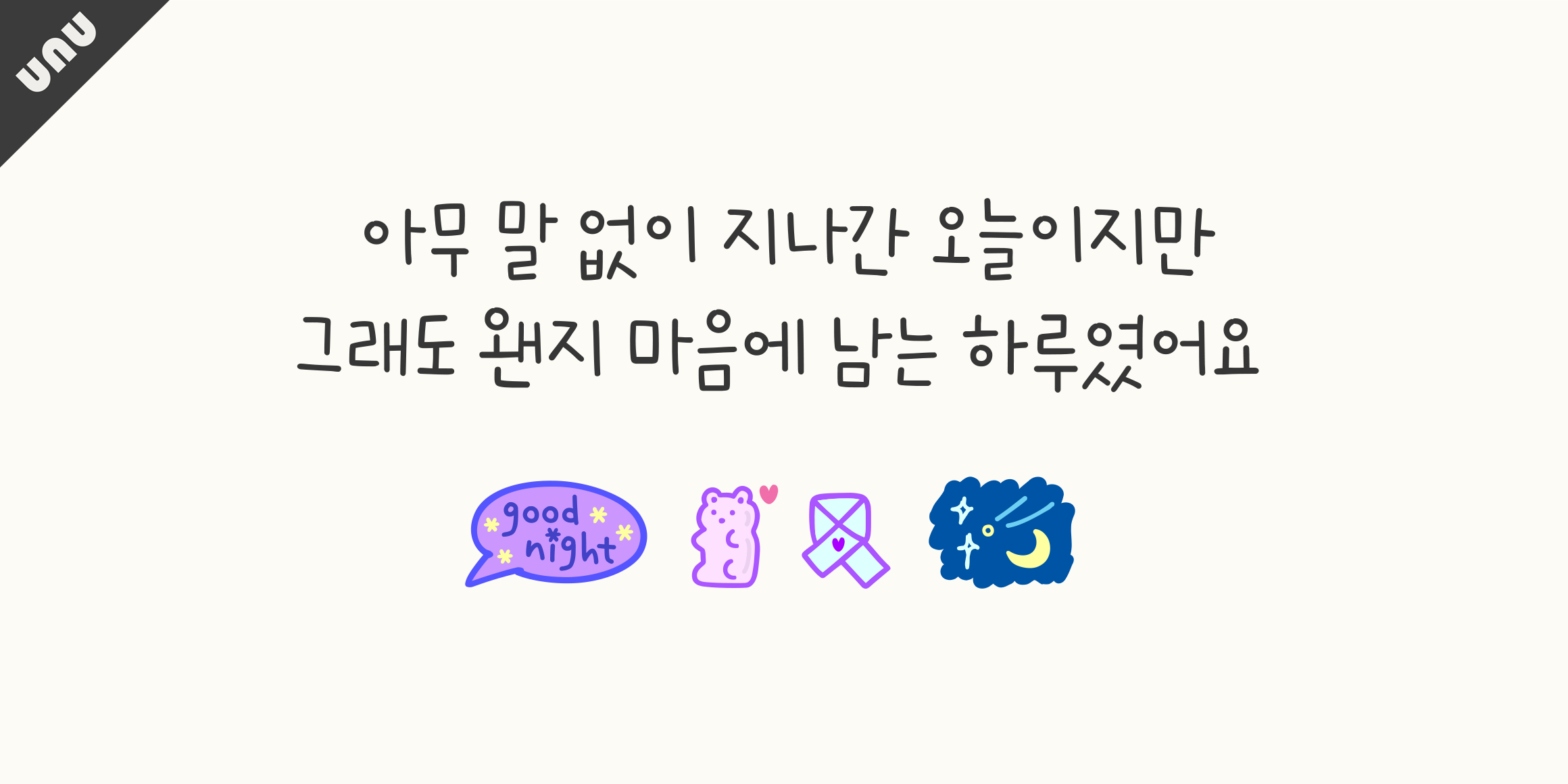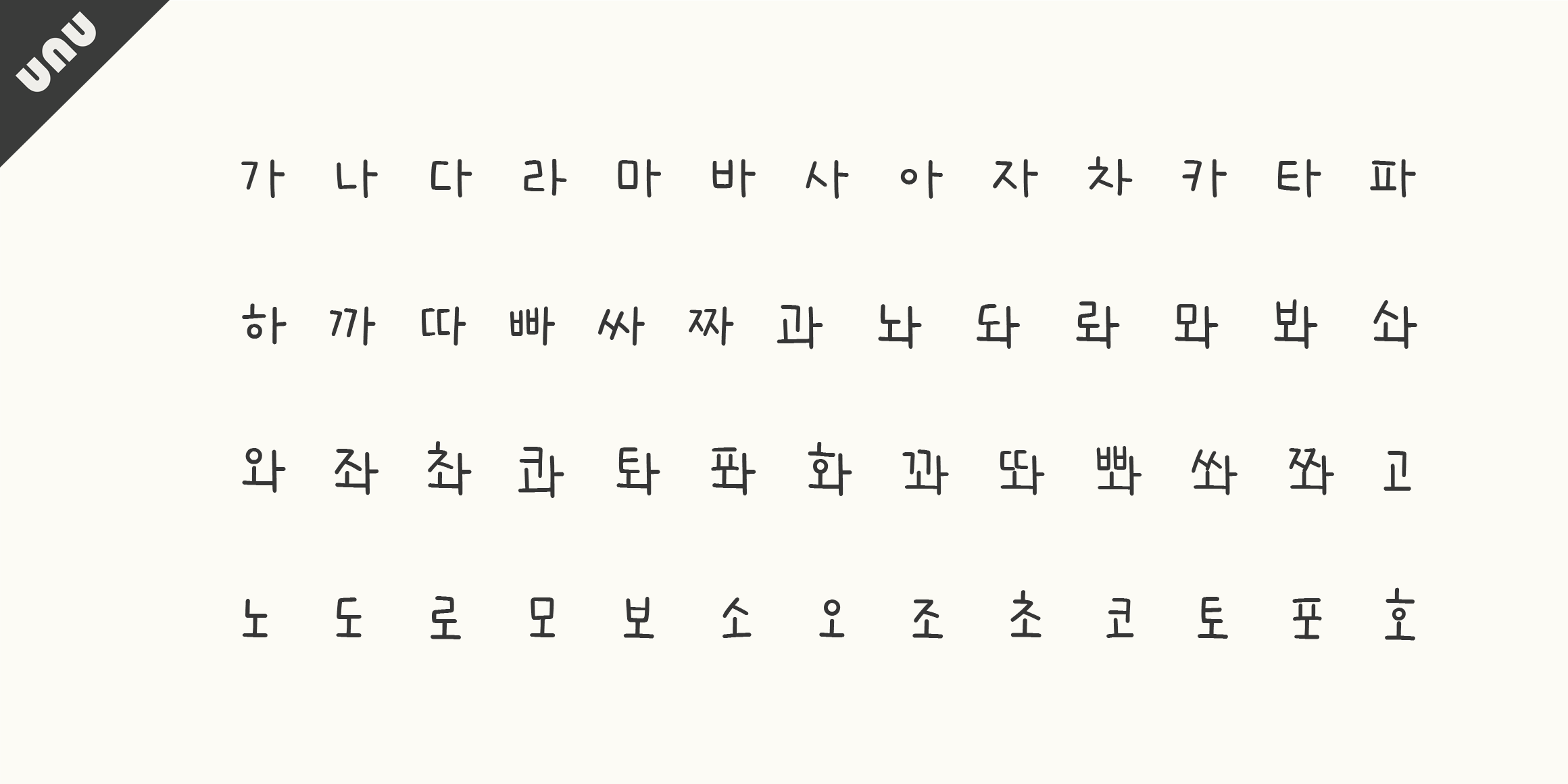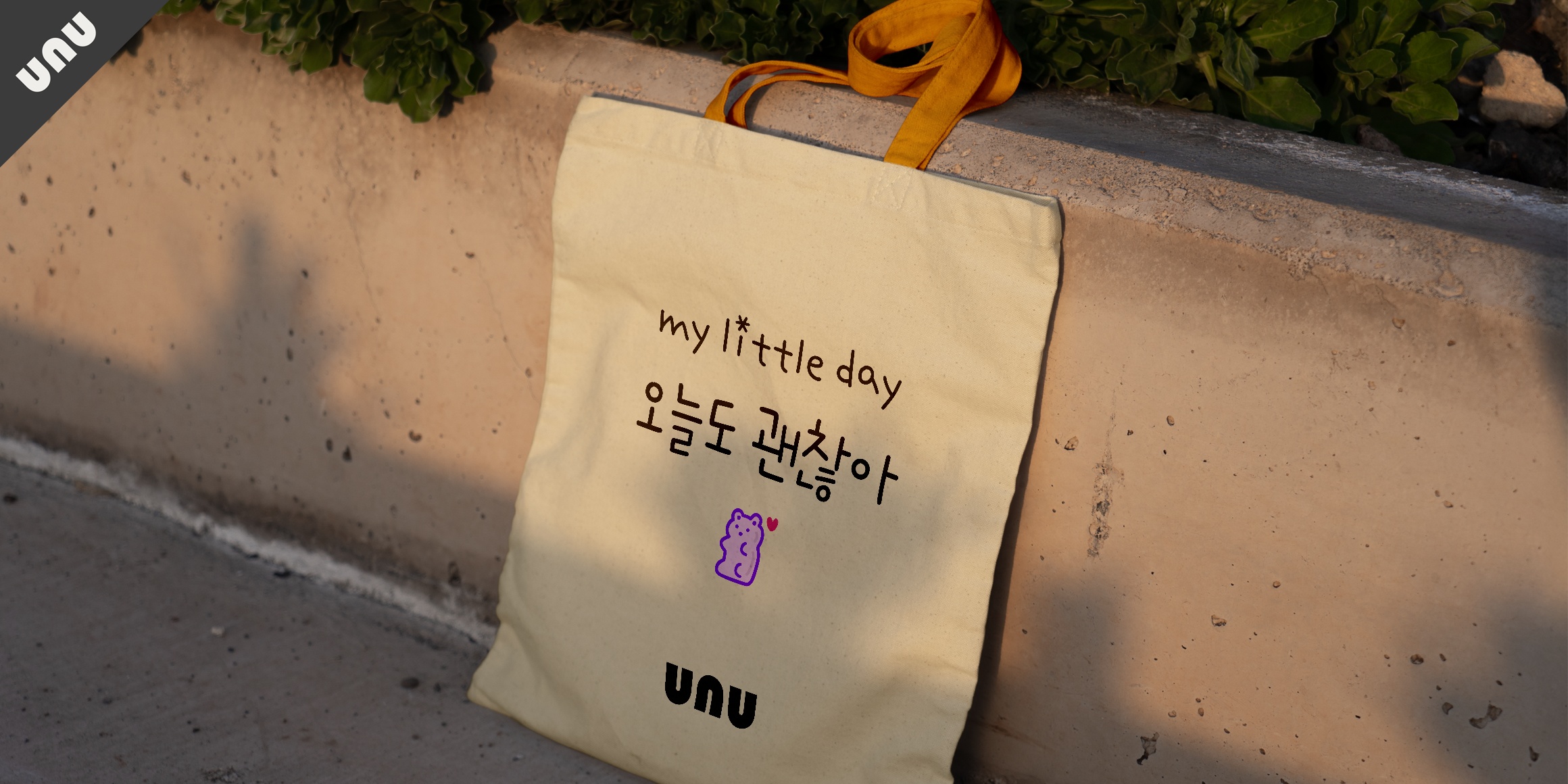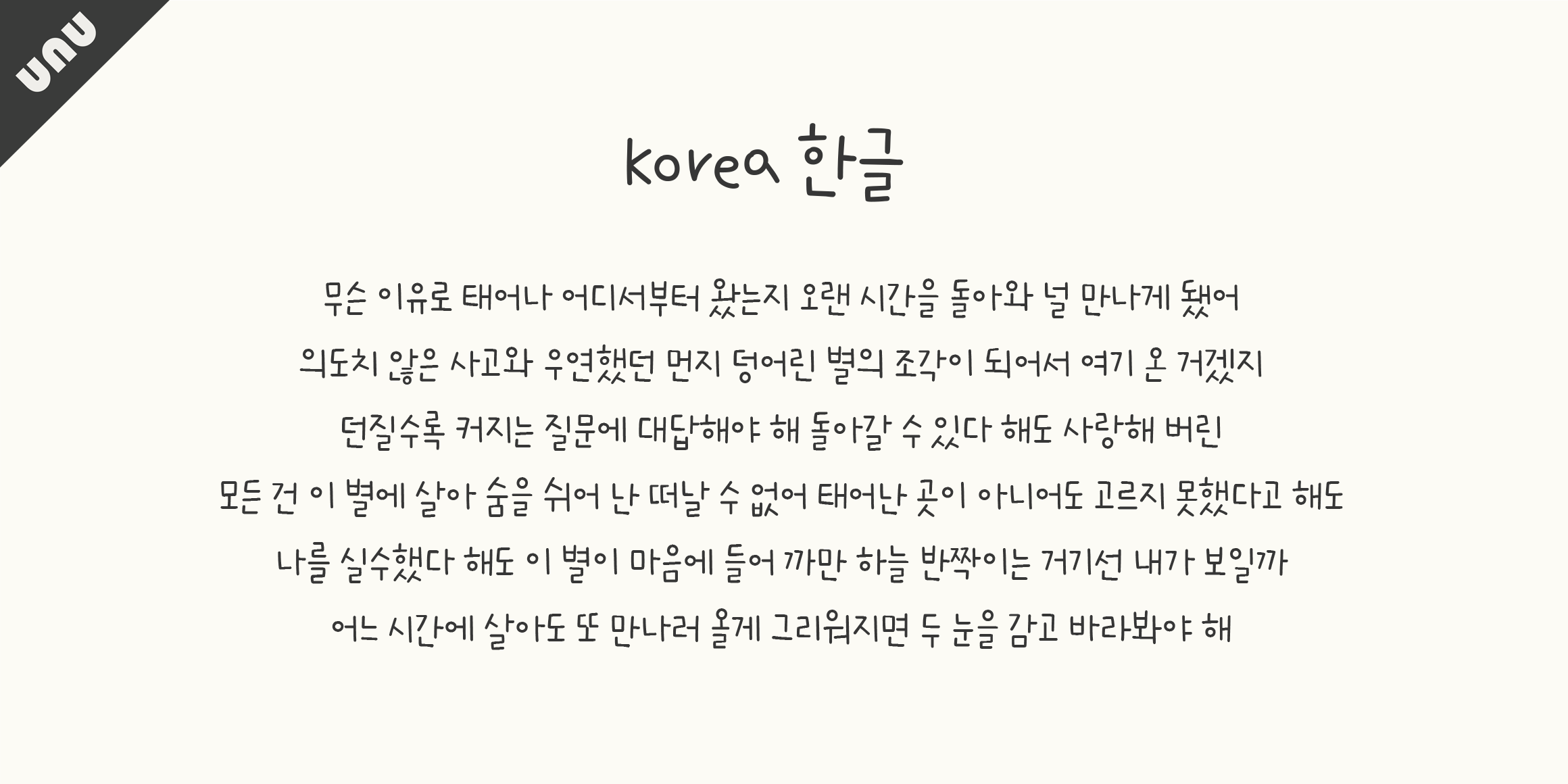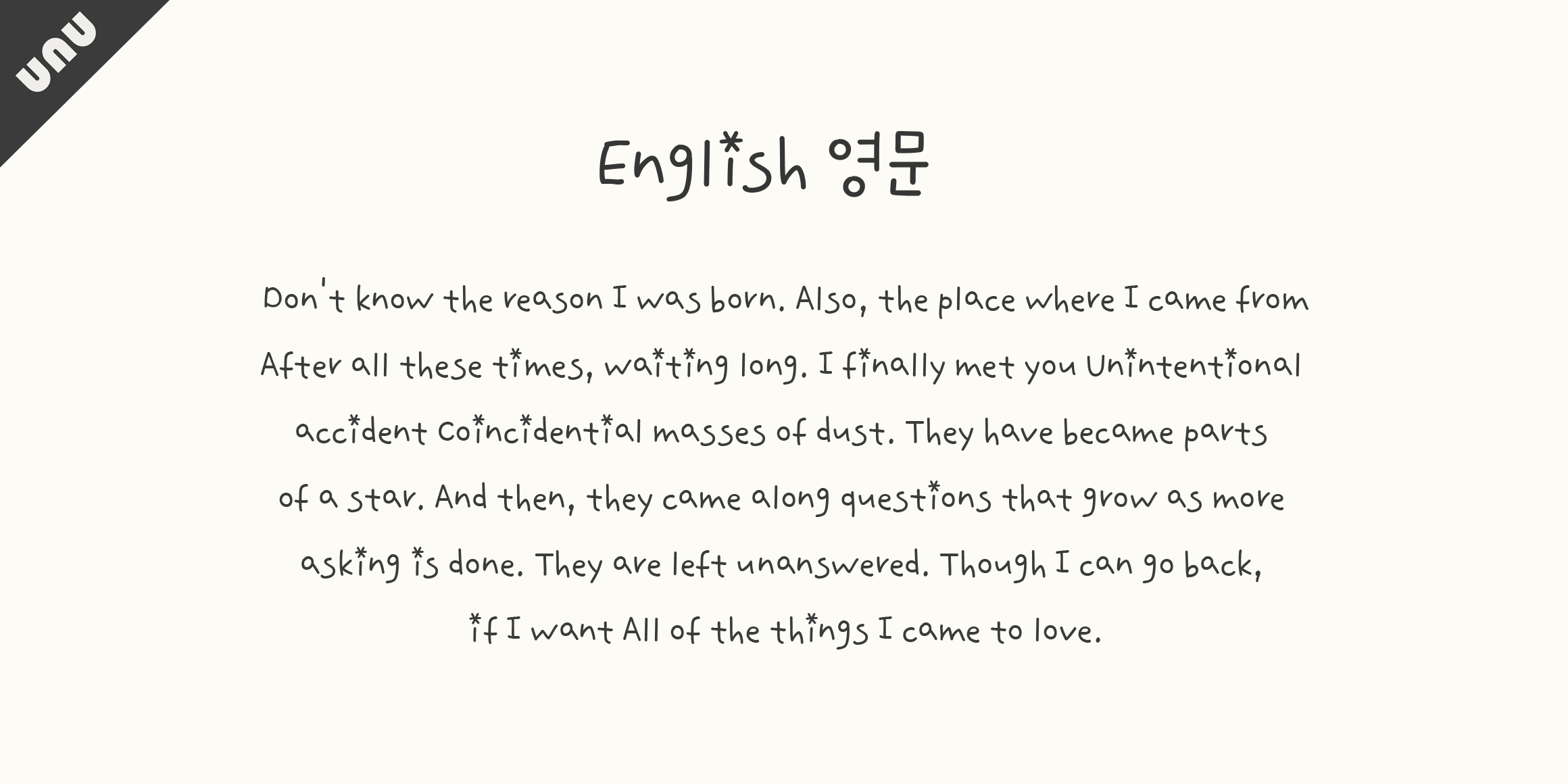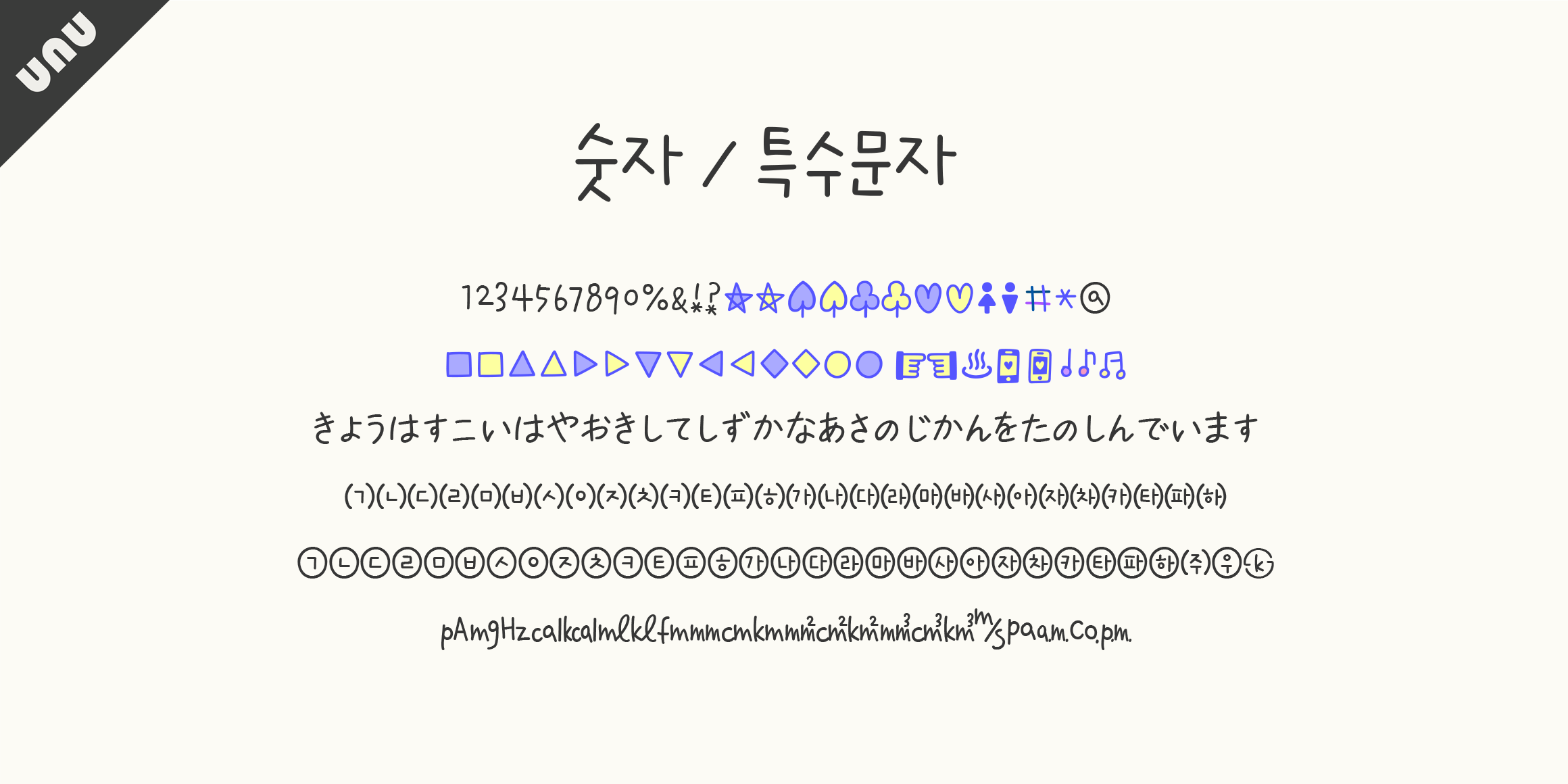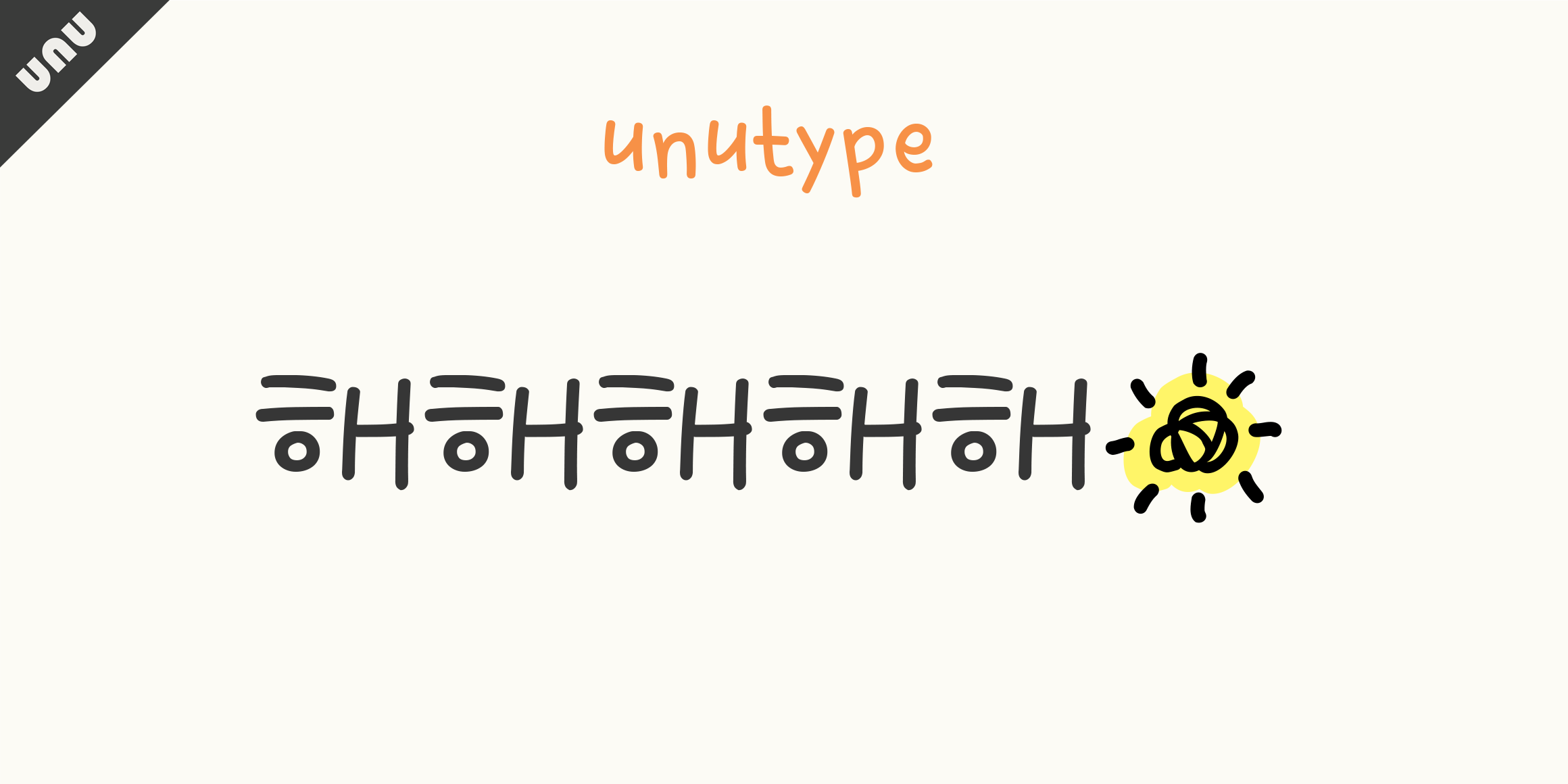
unu별띄운이밤
unu별띄운이밤 font in use
이 서체는 사각사각 반짝이는 별을 담아 적당한 리듬감과 감각있는 자소형태로 제작된 손글씨입니다. 사랑하는 누군가에게 따뜻한 마음을 전하고 싶을때, 내 소중한 다이어리에 오늘을 기록하고 싶을때 추천드립니다. 유앤유서체는 당신의 따뜻한 마음을 전해드립니다.(컬러가 적용되지 않는 기기나 앱이 있을 수 있으며, 두껍게(Bold)처리시 두께 변화가 없을 수 있습니다.)
• Script,손글씨
• unu별띄운이밤 / unustarrynight